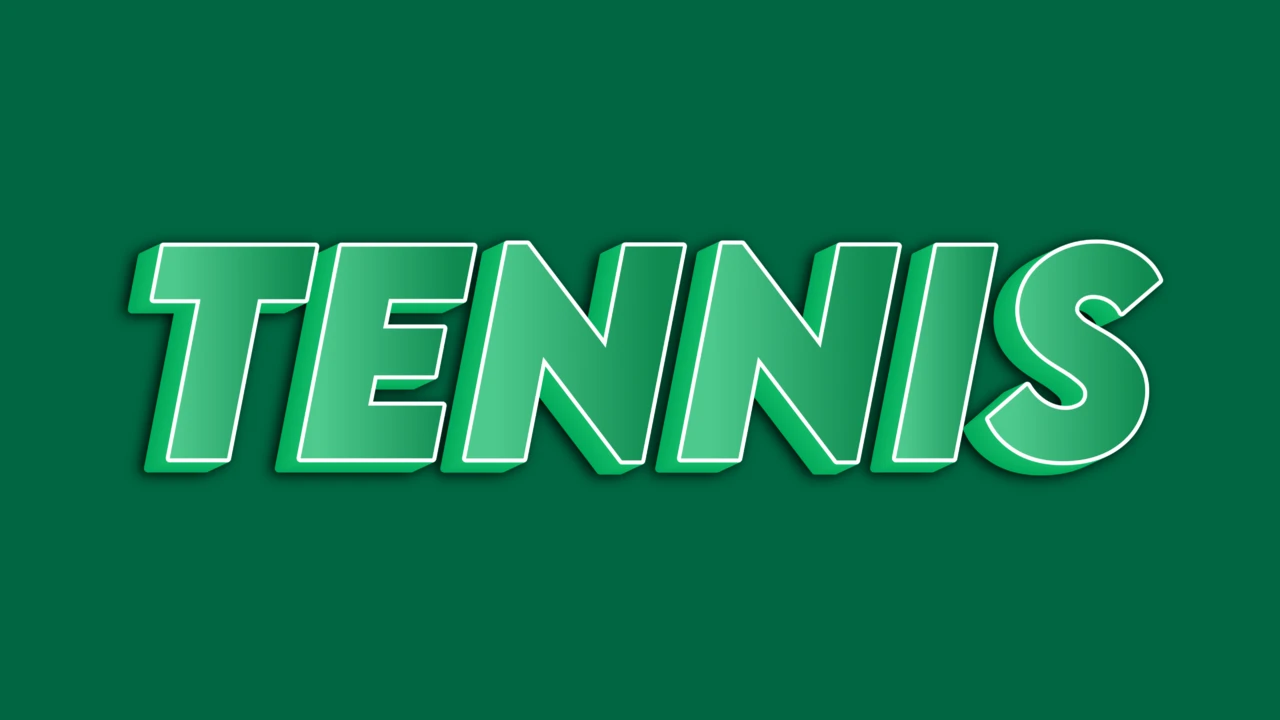
3d groene sportbranding typografie-effect
Geef je ontwerpen een sportieve uitstraling met deze dynamische driedimensionale tekststijl met gedurfde groene tinten en sportieve vibes, perfect voor het creëren van opvallende koppen die elk atletisch of buiten-geïnspireerd brandingproject energie geven.